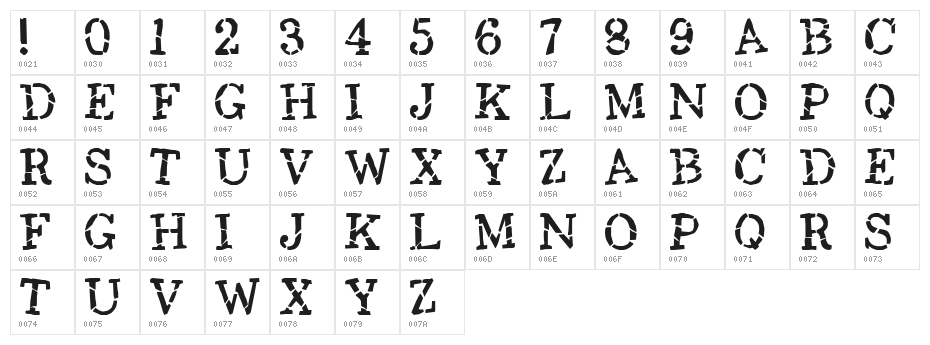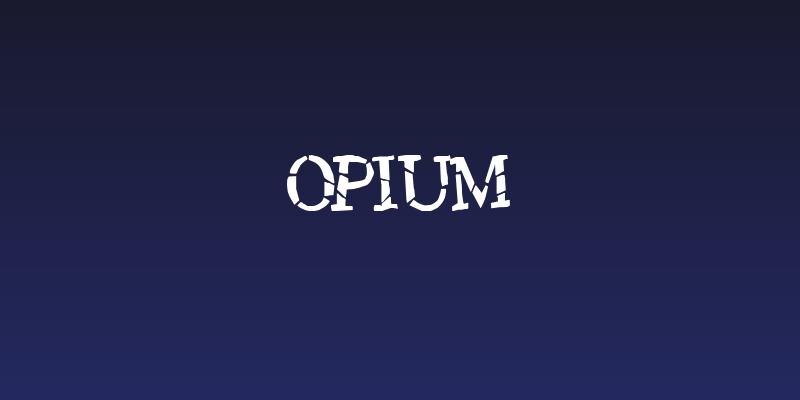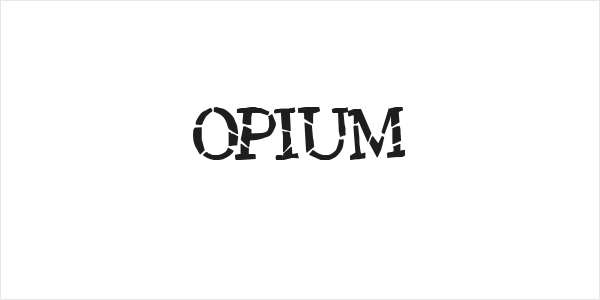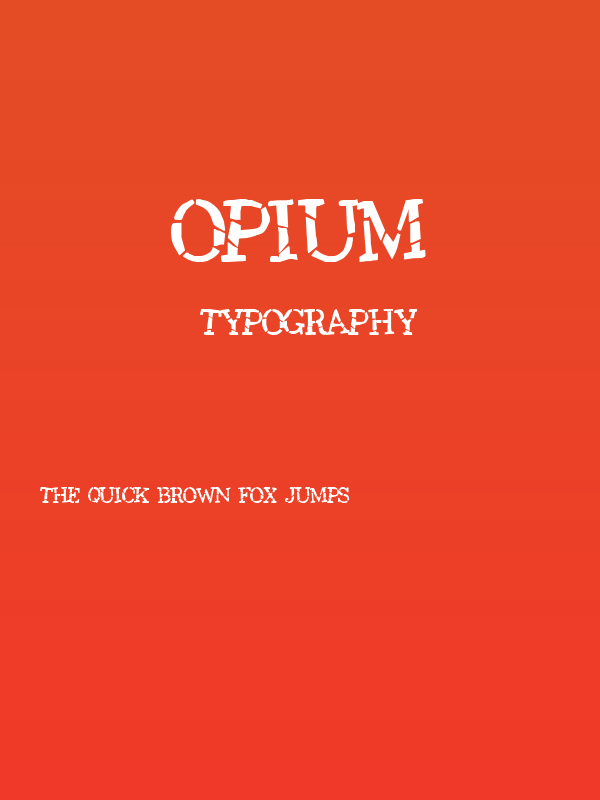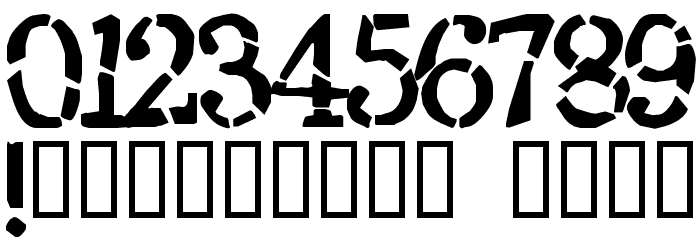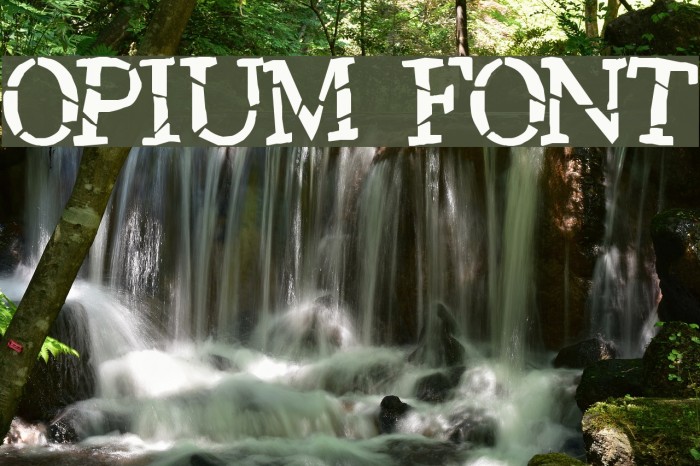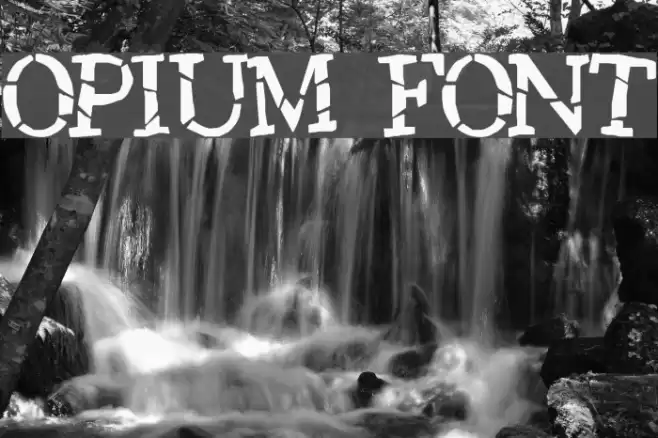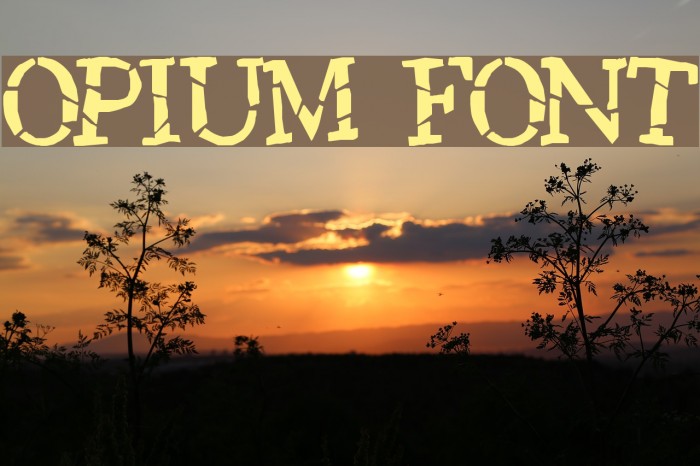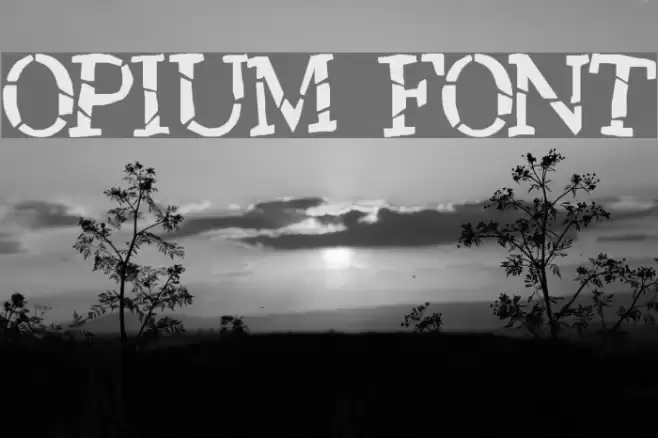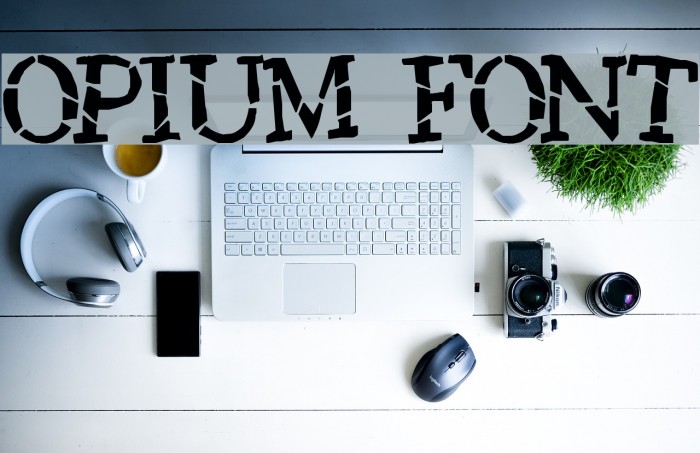
Opium Font
✎ Stencil
| Estilo general | Industrial, Bold, Stencil |
| Caso de uso | Headlines, Signage, Branding |
| Proyectos propuestos | Ideal for posters, signage, branding, and any project requiring a bold, industrial look. |